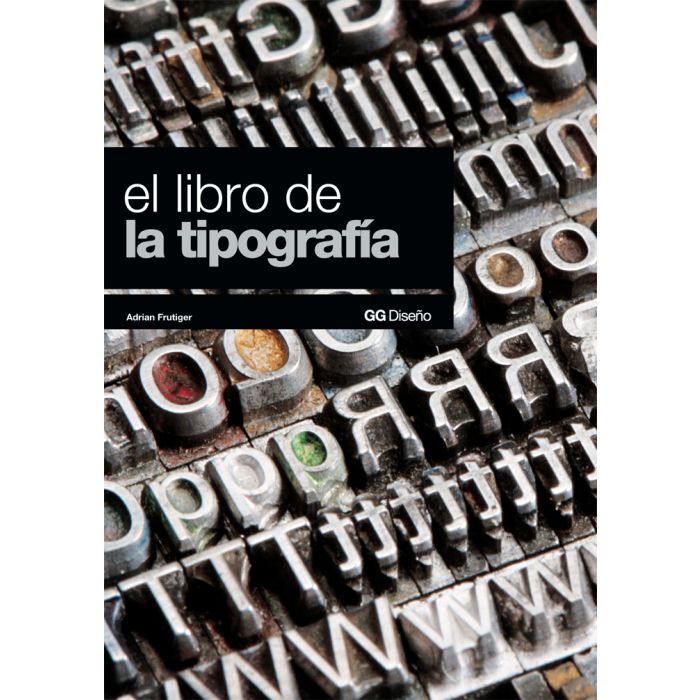
El libro de la tipografía
'Una tipografía debe estar diseñada de tal manera que nadie repare en ella.'
Tras la aparente simplicidad de esta afirmación de Adrian Frutiger se esconden varios decenios dedicados al diseño de tipografías y al estudio de la forma en que los seres humanos interactúan con ellas. Frutiger se niega a concebir la tipografía como un fin en sí mismo, apuesta por subordinar el diseño a su finalidad práctica de servicio a las personas y defiende que el máximo logro al que puede aspirar el diseñador de tipos es que su tipografía pase desapercibida en su lectura.
La tipografía debe estar adaptada a su contexto: 'Las líneas grises de la página de un libro se leen de distinta manera que las letras de una señalización. Hay una enorme diferencia entre leer tranquilamente sentado en el sillón y esperar estresado a embarcar en un avión. En cualquiera de estas situaciones el lector debe sentirse cómodo. Desde ese convencimiento Frutiger exhorta a los jóvenes diseñadores a no dejarse guiar sólo por la creatividad o las modas, sino también por las circunstancias, es decir, por la finalidad de la tipografía y por el entorno en que ésta ha de figurar.
La larga experiencia de Adrian Frutiger se convierte en estas páginas en un material de incalculable valor tanto para los diseñadores como para los profanos que se acercan con curiosidad a este tema.
Texto del prólogo: ‘Prólogo La tipografía adaptada a la vida Las letras como forma suprema de comunicación visual. Visita a Adrian Frutiger Podemos leer porque percibimos e identificamos elementos y formas que nos son conocidos. Además, numerosos aspectos parciales influyen en la lectura de esos elementos que llamamos caracteres de imprenta. Esto que suponemos y comprendemos vagamente es muy familiar para Adrian Frutiger, quien conoce como nadie las relaciones recíprocas que influyen en el proceso de la percepción. Él mismo ha contribuido a la investigación de esas relaciones, que siempre están en la base de sus reflexiones. Su sensibilidad infalible para las formas, su mente analítica, sus conocimientos técnicos y su sentido estético han hecho de él uno de los artistas de la letra más conocidos del mundo. La letra impresa ha llegado a ser algo tan natural y cotidiano para nosotros que apenas la percibimos de manera consciente. Nadie dice cuando abre un periódico por la mañana: ‘¡Ajá, letras impresas!’. Ni siquiera percibe esas letras de una manera consciente, lo cual, según Adrian Frutiger, no es nada malo: todo lo contrario. Pues el que la tipografía empleada no sea percibida como tal ‘es el máximo logro a que puede aspirar el diseñador de tipos y el tipógrafo’. ‘Una tipografía debe estar hecha de tal manera que nadie repare en ella’, dice Frutiger, y lo expresa con una afortunada comparación: ‘Si recuerdas la forma de la cuchara con la que has tomado la sopa, es que esa cuchara tiene una forma inadecuada. Las cucharas y los caracteres de imprenta son instrumentos. Las cucharas sirven para llevar un alimento del plato a la boca, y los caracteres para dar al espíritu un alimento que se encuentra en la hoja impresa.’ Frutiger: omnipresente a través de su obra Esta explicación resulta de gran claridad en medio de su simplicidad. Tras esta comparación en apariencia tan banal, hay varios decenios de dedicación al estudio y el diseño de tipografías y formas, así como al de la conducta humana asociada a ellas. Frutiger nunca ha concebido la tipografía como un fin en sí, sino que siempre la ha puesto al servicio de las personas, es decir, la ha subordinado a su finalidad práctica. Adrian Frutiger ha impulsado de manera decisiva la tipografía, como no podía ser de otro modo tratándose de alguien que siempre ha formado parte de la élite de los diseñadores tipográficos. A pesar de su éxito, la celebridad nunca ha significado nada para él. Facilitar la actividad de leer y trasladar contenidos de la forma más eficiente son los objetivos que se marcó siempre, sin dejarse desorientar por las modas. Casi como ningún otro diseñador, ha llevado a la tipografía las formas visuales de nuestra época. Tipos de letra ya clásicos y usados en el mundo entero, como Univers, Meridien, Avenir, Frutiger, OCR-B o Centennial son sólo una muestra de la rica obra tipográfica de Frutiger en la que se pone de manifiesto que ha estado a la altura de su época. Los amigos y admiradores del tipógrafo suizo siempre han coincidido en que Frutiger, en sus fuentes tipográficas y sus trabajos artísticos, ha logrado como ningún otro dotar a las corrientes de la época de unas formas discretas, útiles, razonables, armónicas y prácticas, sin deslizarse jamás hacia lo banal. Para Bruno Steinert, director de la Linotype Library, la obra y la influencia de Frutiger han hecho época: ‘Adrian Frutiger está omnipresente a través de su obra tipográfica -hasta en los rincones más apartados del globo-. Su creación ha dejado una marca indeleble en el mundo de la comunicación’. Steinert tiene razón: basta recordar todos los tipos de letra que Frutiger creó. Ya en 1994 observó Kurt Weidemann: ‘Su creación tipográfica comprende un número apreciable de alfabetos en uso que sobrevivirán a todos esos volúmenes de muestras tipográficas, gruesos como guías telefónicas y llenos de banalidades y arbitrariedades’. Pero, con toda su merecida fama -si bien lamentablemente casi confinada en los círculos especializados-, Adrian Frutiger sigue siendo un hombre cuya modestia nos admira: ‘No tengo ninguna aureola. Siempre fui un hijo de mi tiempo y eso no podía cambiarlo’, declaró en su 70 aniversario. Y aún hoy, a sus 76 años, Adrian Frutiger es capaz, en una conversación en la que no se observa el más mínimo gesto de autocomplacencia, de hechizar, fascinar, transportar a su interlocutor a otro mundo y hacer de una materia como la tipografía (árida para muchos) un universo de inagotables historias y anécdotas. Tipografías acordes con su finalidad ‘La tipografía debe ser tan bella como un bosque, no como el desierto de hormigón de un arrabal. Un bosque no es ninguna aglomeración, sino que hay distancias entre los árboles, que proporcionan un espacio para respirar y vivir.’ Lo mismo la tipografía. Si es demasiado estrecha, no puede reconocerse. ‘No deja respirar al lector’, dice Frutiger. Por eso insiste siempre en que la tipografía ha de adaptarse a su entorno: ‘La tipografía debe ser reconocible en fracciones de segundo’. Y ello, piensa él, prácticamente en todas las situaciones. Nadie como él ha creado tipografías para la composición, libros, guías y toda clase de diseños y, a la par, diseñado letras para indicadores dispuestos en espacios públicos. ‘Las líneas grises de la página de un libro se leen de otra manera que las letras de una señalización. Hay una enorme diferencia entre leer tranquilamente sentado en el sillón y esperar estresado a embarcar en un avión’ Pero se halle donde se halle, ‘el lector debe sentirse cómodo’, declara, pues las letras no deben producir malestar o estrés. Frutiger llevó a cabo profundos estudios de todas las tipografías (incluidas las suyas), y llegó a la conclusión de que las letras usadas en los libros, aunque se amplían al máximo, resultan demasiado cerradas para los letreros de los aeropuertos o las autopistas. Por eso modificó su Univers para adaptarla, por ejemplo, a los indicadores del aeropuerto Charles de Gaulle de París. ‘Una tipografía se compone de elementos blancos y negros: la estructura de la letra, los blancos internos y los espacios entre letras. Las letras empleadas en indicadores deben cumplir, en cuanto a la forma, otros requisitos que las que encontramos en un libro. Cuando se viaja en coche, se corre o se anda, el signo ha de ser reconocible instantáneamente’, afirma Frutiger. Sus fuentes tipográficas creadas a este fin contienen letras y signos abiertos que se reconocen fácilmente, están hechos para ser leídos al instante y sin confusiones. ‘Una letra debe ser tan clara como una flecha’, afirma Frutiger, y esta frase expresa todo lo que hay que decir sobre el tema. Las rotulaciones que no se entienden al primer golpe de vista sirven para confundir más que para aclarar u orientar. Y esto en todos los ámbitos. También en las señales de tráfico de las carreteras suizas reconocemos la letra de Frutiger. En este caso, no se empleó para la señalización una tipografía ya existente. Frutiger diseñó una tipografía completamente nueva, que permitía una legibilidad óptima de las letras que aparecen en las señales. En esta tipografía, la Frutiger Astra, Frutiger agrandó sobre todo los espacios internos. De ese modo, pueden distinguirse claramente letras como la a o la e, mientras que con los tipos de letra anteriormente usados sólo se veía un punto blanco. ‘El automovilista se metía, por así decirlo, en un agujero blanco’, dice Adrian Frutiger. Las tareas se presentan ellas solas Adrian Frutiger no es uno de esos artistas que habitan en una torre de marfil y de vez en cuando reciben la visita de la musa. Tampoco le venía la inspiración únicamente de dentro (de sí mismo), sino que continuamente encontraba problemas, relativos al trato diario con las letras, que demandaban soluciones. A este respecto cuenta Frutiger una anécdota que revela lo que para él es la tarea de un creador de alfabetos: ‘Hace algunos años, encontrándome en la estación, vi a una mujer mayor que intentaba leer un horario de trenes. No conseguía descifrarlo debido a que la letra era demasiado pequeña. Mientras la ayudaba me vi de repente frente a un reto: el de crear una nueva tipografía que fuera la idónea para estos casos’. Así nació el alfabeto Vectora, una tipografía con trazos medios muy grandes que puede leerse muy bien incluso empleando cuerpos muy pequeños. Y en este contexto Frutiger exhorta a los jóvenes creadores que trabajan en agencias y estudios de diseño a no dejarse guiar sólo por la creatividad, sino también por las circunstancias, es decir, por la finalidad de la tipografía y por el entorno en que ésta ha de figurar. ‘Las letras deben aparecer despejadas y claras. Deben adaptarse a la vida, pues ellas son el vestido de la palabra. Por eso deben subordinarse al contenido de la lectura.’ ¿Los últimos de su gremio? En este contexto, Frutiger constata que en la actualidad hay muchos diseñadores que juegan en la pantalla del ordenador, pero no inventan nada nuevo: ‘Se reforman las letras, pero no se crean desde el principio. Entre estos jóvenes hay algunos muy dotados que comprenden lo que es el fluir de las letras -otros sólo creen entenderlo-’. Cabe preguntarse si Adrian Frutiger y Hermann Zapf -a quien no hay que dejar de nombrar aquí- son los últimos de ‘su gremio’ que han creado fuentes tipográficas capaces de entusiasmar a las generaciones venideras. ‘Yo no lo creo’, declara Frutiger. ‘Nuestra base era y es la tipografía hecha para la lectura, sobre todo la utilizada en los medios impresos. Pero siempre habrá personas competentes y capacitadas para renovar los materiales básicos y crear cosas nuevas.’ Personas altamente dotadas, como él dice, con un interés especial por algo determinado. Frutiger siempre vio y sigue viendo su tarea principal en la elaboración de fuentes tipográficas sin remates -incitado por sus maestros Walter Käch y Alfred Willimann en la Escuela de Artes y Oficios de Zúrich-. ‘Lo que mejor iba con mi carácter era centrar mi trabajo en las tipografías sin remates. Esto tenía relación en parte con los trabajos que me encargaban, pero también con muchas otras cosas de orden técnico que yo había aprendido.’ Pero Frutiger no sólo creó tipografías para personas, sino también para máquinas. ‘Porque el ojo funciona de manera análoga a una computadora, o, mejor dicho, a un aparato lector gobernado por una computadora.’ Adrian Frutiger desarrolló en los años setenta la tipografía OCR–B, que aún hoy se emplea en las tarjetas de crédito y en las trans- ferencias y cheques bancarios; no existe otro tipo de letra que una computadora pueda leer mejor. Del mismo modo que ha creado nuevas tipografías para nuevas funciones, Frutiger no duda de que los cambios en los medios materiales traerán consigo nuevas tareas y nuevos retos. ‘Los cambios se producirán de forma inesperada. Pero entonces habrá otros tipógrafos que tomarán como científicos nuevos caminos nunca antes recorridos.’ No da ejemplos, pero todos sabemos que aún hay bastantes tareas pendientes que la tipografía -las nuevas creaciones tipográficas y las nuevas ideas- sin duda podrá abordar. Un buen ejemplo es Internet, donde reina la pobreza tipográfica. Pero hay también otros dominios, como el de la televisión, en los que es urgente cambiar las cosas. Los nuevos medios, concluye Frutiger, requieren nuevos instrumentos. Frutiger: un perfeccionista Como asesor, Adrian Frutiger no sólo crea tipografías propias, sino que también realiza nuevos conceptos e inicia nuevas tendencias. En ellos no siempre ha de estar presente la tipografía no formal, objetiva, pues Frutiger es bien consciente de la necesidad de una expresión viva y de una variedad de formas en el papel impreso. ‘La propia letra es una imagen. Por eso no tengo nada contra las letras de fantasía.’ Él mismo creó hace unos años una nueva tipografía, la Frutiger Stones, que es más moderna y a la vez más rudimentaria que lo que incluso los ‘jóvenes rebeldes’ de la tipografía producen actualmente. Porque Adrian Frutiger sabe tomar las corrientes actuales de una manera genial y combinarlas con los recursos estilísticos más eficaces presentes en las antiguas percepciones humanas de las imágenes y las formas. Frutiger demostró su capacidad de autocrítica ante los continuos cambios en el mundo de los medios cuando reelaboró, mejoró y complementó para la Linotype Library su tipografía Univers, que fue su mayor éxito. Fruto de aquella labor fueron 59 formas, cada una, una obra maestra. ‘La tipografía Univers de Adrian Frutiger es, sin discusión, la más importante de los últimos cien años’, ha dicho Bruno Steinert, director de la Linotype Library. En 1977, Frutiger reelaboró y amplió también su tipografía Frutiger, que pasó a llamarse Frutiger Next, con el fin de hacerla accesible sobre todo para la comunicación empresarial y en los espacios públicos, y para los sistemas de información. Las 18 formas que comprende no parecen realizadas con un sistema constructor, sino que fueron diseñadas individualmente e incluso con formas distintivas. Formas y contraformas A quien estudia las tipografías de Frutiger no le sorprenden sus trabajos libres de naturaleza artística. Muchos dibujos, grabados y objetos dan una idea de la creatividad artística de Adrian Frutiger al margen de la tipografía. En ellos, el lenguaje formal de Frutiger que aparece en los signos se distingue por una austeridad extrema en cuanto a las formas y los colores, como la de los signos tipográficos, que no pueden ser más abstractos. Frutiger creó estas formas libres ‘simplemente para relajarse’ y busca en ellas símbolos para nuestra época. Son signos, señales y formas perfectamente definidas gráficamente que, además de poseer cualidades estéticas, son signos elementales, signos para la meditación, signos filosóficos que cada cual puede interpretar a su manera y que dejan en cada persona una impresión distinta. En estas obras, Frutiger complementa su creación tipográfica en una dimensión estética: esas formas libres, desligadas del alfabeto, muestran su concepto de la relación armónica entre el blanco y el negro, entre colores intencionadamente discretos y entre formas internas y externas que entrañan un sentido filosófico. (Estos trabajos están documentados en el libro Hommage à Adrian Frutiger, que contiene unas 250 reproducciones, y ha sido publicado por la editorial Syndorpress, de Cham, Suiza.) Dar y tomar En la actualidad, Adrian Frutiger está trabajando sobre todo en un nuevo libro que aparecerá en el próximo otoño. ‘Es parte de una reflexión que llevo haciendo desde hace bastante tiempo: dar y tomar. En esto no hay nada de revolucionario: antes de ahora, el hombre mayor enseñaba al joven, el padre al hijo, la madre a la hija, el maestro a los aprendices... Un continuo dar y transmitir, y naturalmente, también un continuo recibir y tomar, distinguía a estas relaciones.’ Sin duda, muchos pensarán que este sistema ya no vale, reconoce Frutiger, porque los jóvenes, sentados ante el PC, se cierran a otras influencias. A lo cual responde Frutiger que (si no se equivoca) hay claros signos de que las cosas van a cambiar. ‘La época en que se pensaba que el ordenador podría hacerlo todo ha pasado. Es una idiotez creer que el ordenador pueda reemplazar a las manos. ¡Un ordenador jamás podrá construir un violín que suene!’. Y prosigue: ‘¿Por qué va la gente a los conciertos? ¿Por qué hace excursiones? ¿O por qué medita? Porque el rumbo que la era del ordenador quiere marcar es antinatural para los seres humanos’. Frutiger está convencido firmemente de que la era del ordenador no impedirá las relaciones comunitarias y la comunicación. ‘Con la revolución técnica, muchas cosas han sufrido cambios esenciales’, dice Frutiger. ‘La inteligible sencillez de la imprenta se disolvió en docenas de fases de redacción, composición, copia e impresión. Sin el trabajo en equipo, la producción de cualquier cosa impresa es ya inimaginable.’ Frutiger contempla esta evolución con mirada crítica, pero en modo alguno con resignación, pues, piensa: ‘Todo lo presente está construido sobre la experiencia del pasado. Por tanto, el futuro existe ya en el presente’. Así pues, el pasado es para Adrian Frutiger componente esencial de nuestro presente. De ahí su intención de dejarnos su legado en forma de libro. Porque también es su intención conservar en él cosas que de otro modo podrían perderse. Y así nos describe habilidades artesanales como, por ejemplo, la entalladura de punzones y las técnicas empleadas en el pasado. ‘Quiero transmitir a otros todo lo que he aprendido y vivido, y todo lo que considero relevante. Este saber se perderá si ni siquiera queda documentado.’ La palabra escrita: parte de nuestra cultura Es perfectamente comprensible que Adrian Frugier quiera transmitir este legado en forma de libro, pues su nombre está y seguirá estando vinculado a la tipografía: ‘Estoy convencido de que la palabra escrita continuará manteniéndose en los siglos venideros como el instrumento mediador entre quien tiene algo que decir y quien quiere conocer ese algo. No puedo imaginar que esto pueda acontecer exclusivamente a través de imágenes. En nuestro ambiente, la tradición oral está atrofiada, y las imágenes desempeñan un papel cada vez más importante, pero la historia de Europa está marcada por la palabra escrita. Lo ha estado durante milenios, y ello ha arraigado profundamente en nosotros. Por ello, la palabra escrita es y será parte de nuestro estilo de vida.’ Y una idea más de Adrian Frutiger que debería hacer reflexionar a todos los que se ocupan en el diseño: no dar demasiada importancia a la moda y a las continuas veleidades del diseño y considerar las cualidades de la letra, la imagen, el diseño y los medios desde un punto de vista muy pragmático: ‘La tipografía y el diseño que vemos no cumplen su función porque se apartan del contenido’. Este diagnóstico refleja el carácter de Frutiger. Lo que amigos y socios especialmente estiman de él son las hoy bien raras cualidades del sosiego y la concentración, la consecuencia y la modestia, el dinamismo y la perseverancia, la perspicacia y el pragmatismo. A sus 76 años conserva su flexibilidad intelectual, irradia en la conversación claridad mental, y es capaz de transmitir de forma plástica y comprensible sus conocimientos fundamentales y sus visiones. Klaus-Peter Nicolay’ Copyright del texto: sus autores Copyright de la edición: Editorial Gustavo Gili SL |